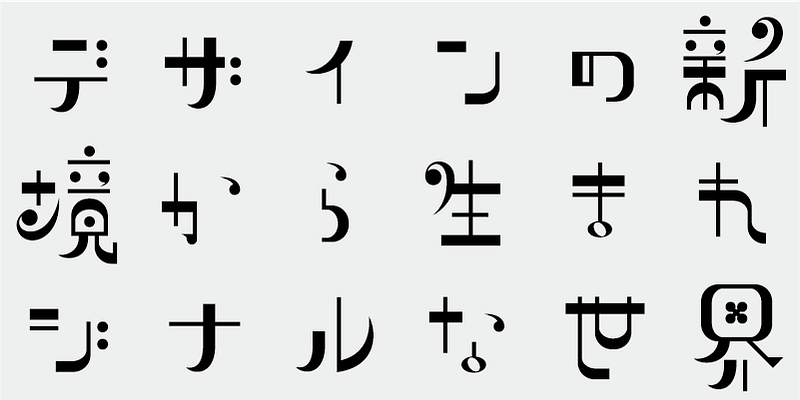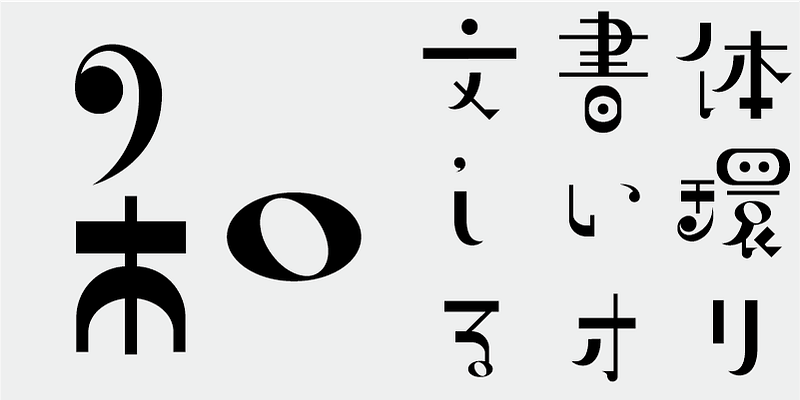
Il motivo del design di questo carattere tipografico sono i simboli musicali. Gli elementi dei simboli musicali sono disposti in modo sbilanciato per formare delle lettere. Ciò conferisce al testo impostato nel carattere tipografico un ritmo visivo confortevole.
Questo adorabile carattere tipografico ti farà sentire come se stessi camminando in un parco.
Questo carattere tipografico di visualizzazione è efficace per titoli di film o programmi TV, design di pacchetti, testi pubblicitari accattivanti e così via.
Questo font include i primi 1.000 caratteri kanji scelti dalle tabelle di frequenza dei caratteri realizzate da società di giornali, case editrici e istituti di ricerca linguistica, oltre a 206 caratteri kana e segni di punteggiatura.
Nella produzione odierna di font giapponesi, i 7.000 caratteri nello standard JIS sono considerati essenziali. Ma tutti i font hanno davvero bisogno di 7.000 caratteri? Nell’era della fotocomposizione, erano necessari molti meno caratteri. FONT1000, un gruppo di progettisti di caratteri indipendenti, ha iniziato con questa semplice domanda. Abbiamo selezionato il minimo di 1.000 caratteri kanji (ideografici) necessari per la composizione in giapponese e abbiamo creato attivamente caratteri tipografici e font per supportarlo. Questo set di 1.000 caratteri kanji è stato selezionato utilizzando dati sulla frequenza dei caratteri compilati da società di giornali, case editrici e organizzazioni di ricerca linguistica, e così via e include anche caratteri sillabici kana e segni di punteggiatura. FONT1000 è stata costituita nel 2001 con 25 progettisti e 25 caratteri tipografici. Oggi abbiamo 130 caratteri tipografici e siamo cresciuti fino a includere circa 40 membri, rendendo possibile lavorare su font con più caratteri.